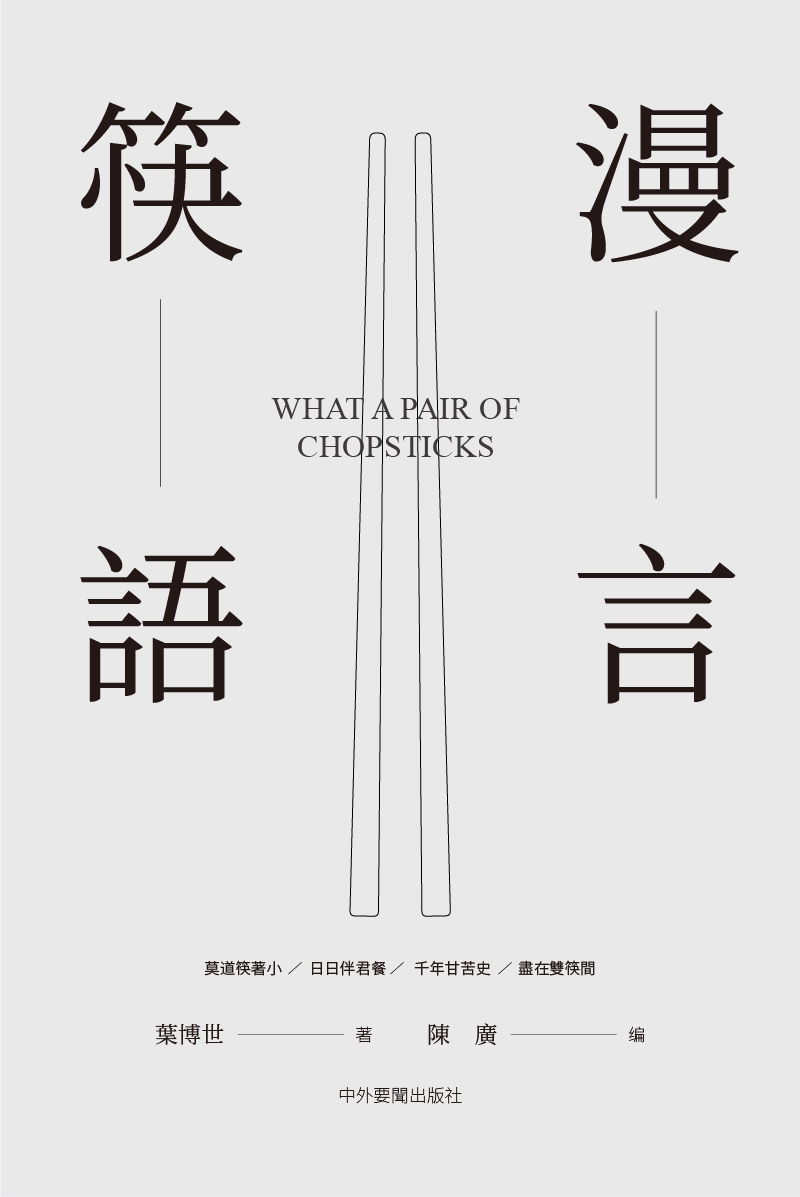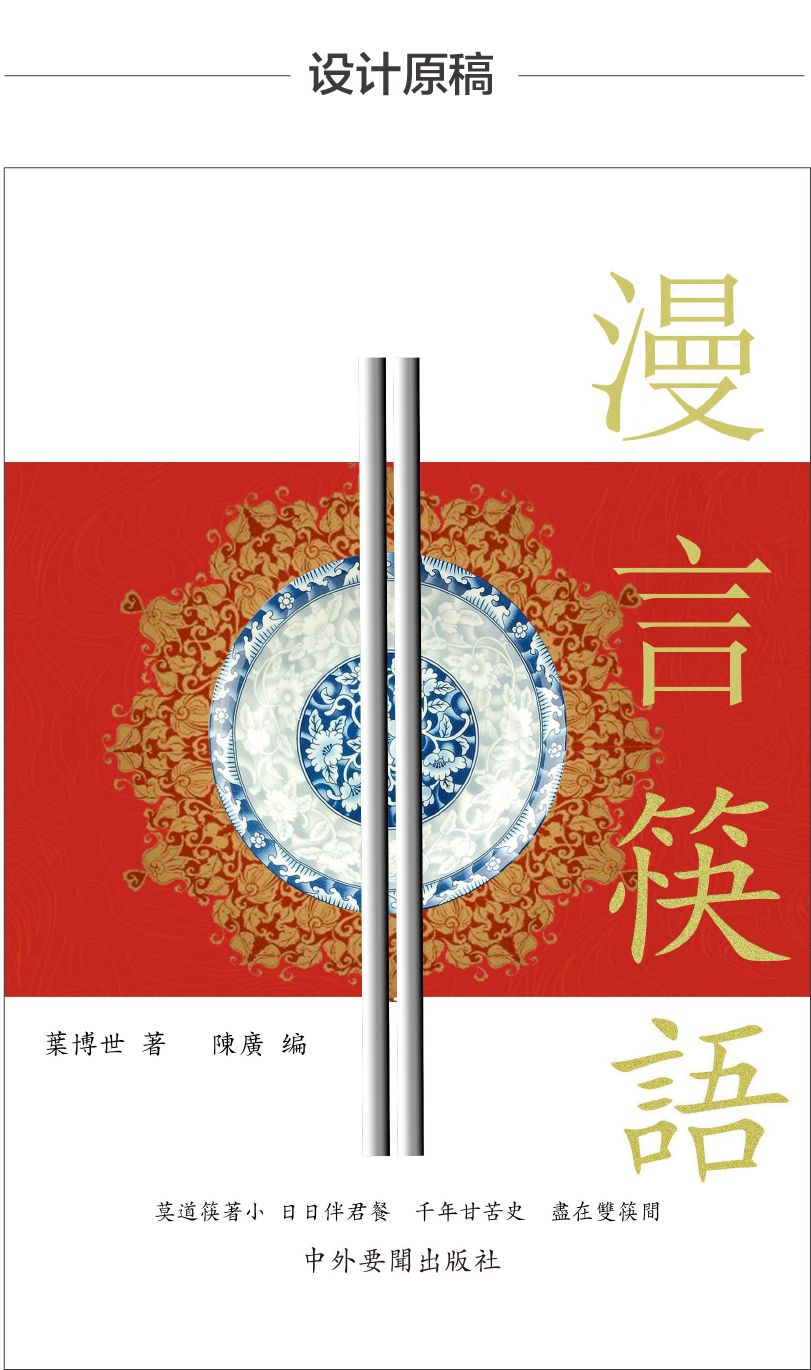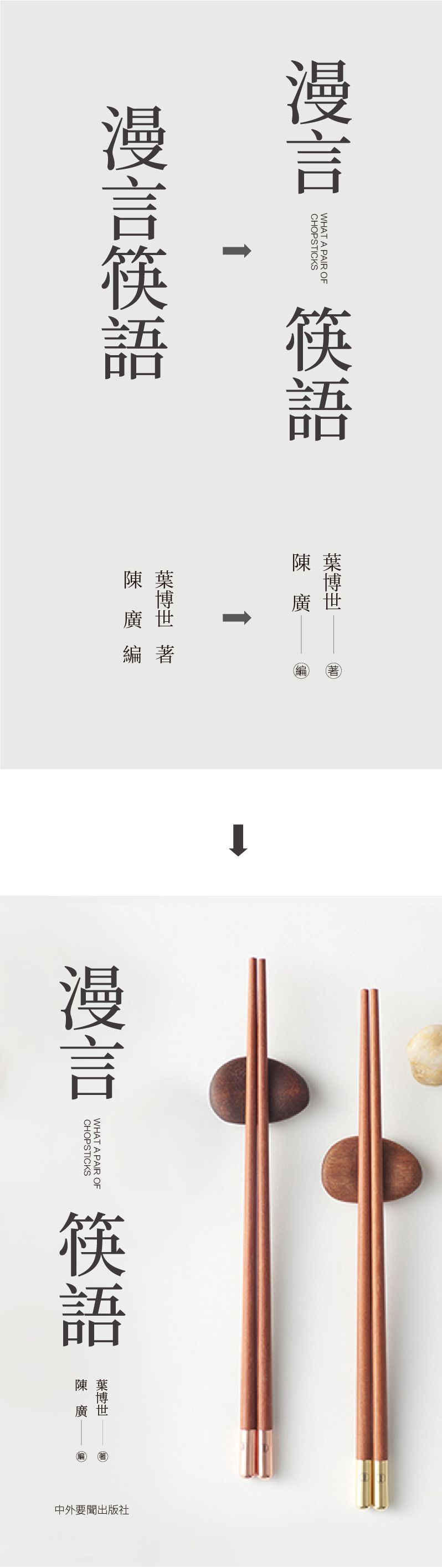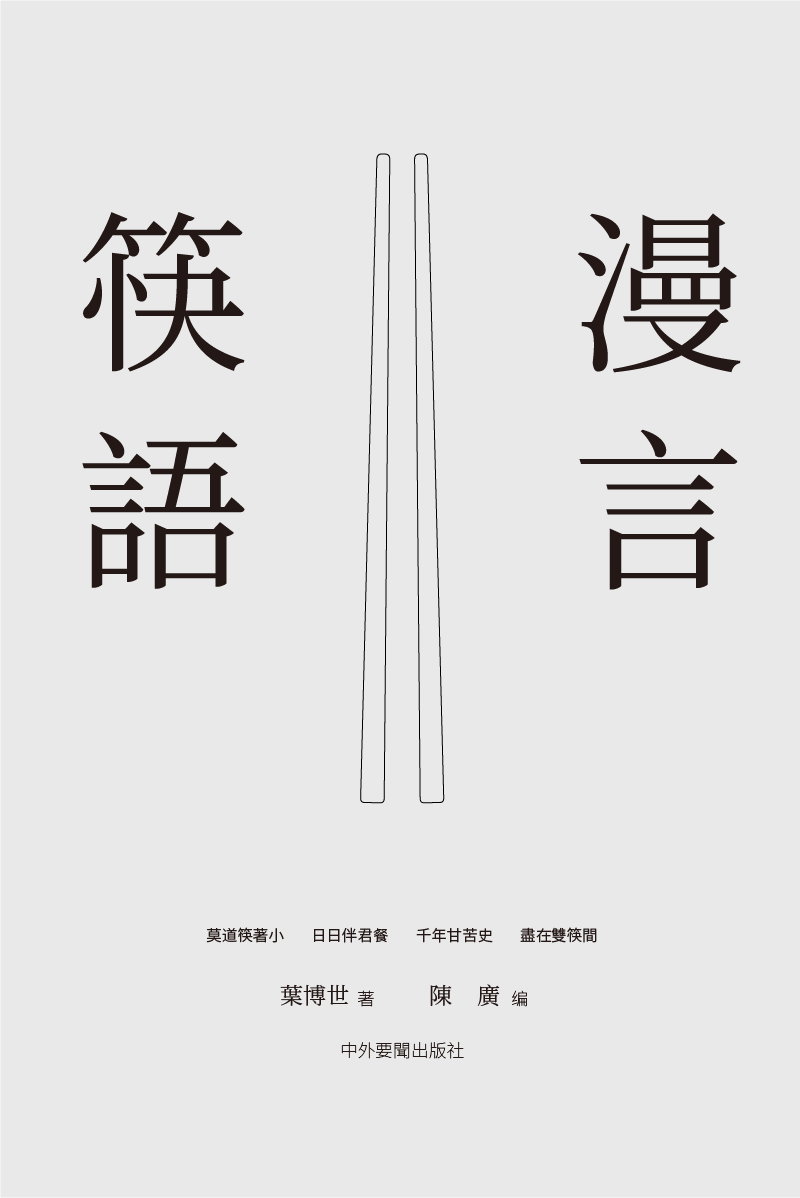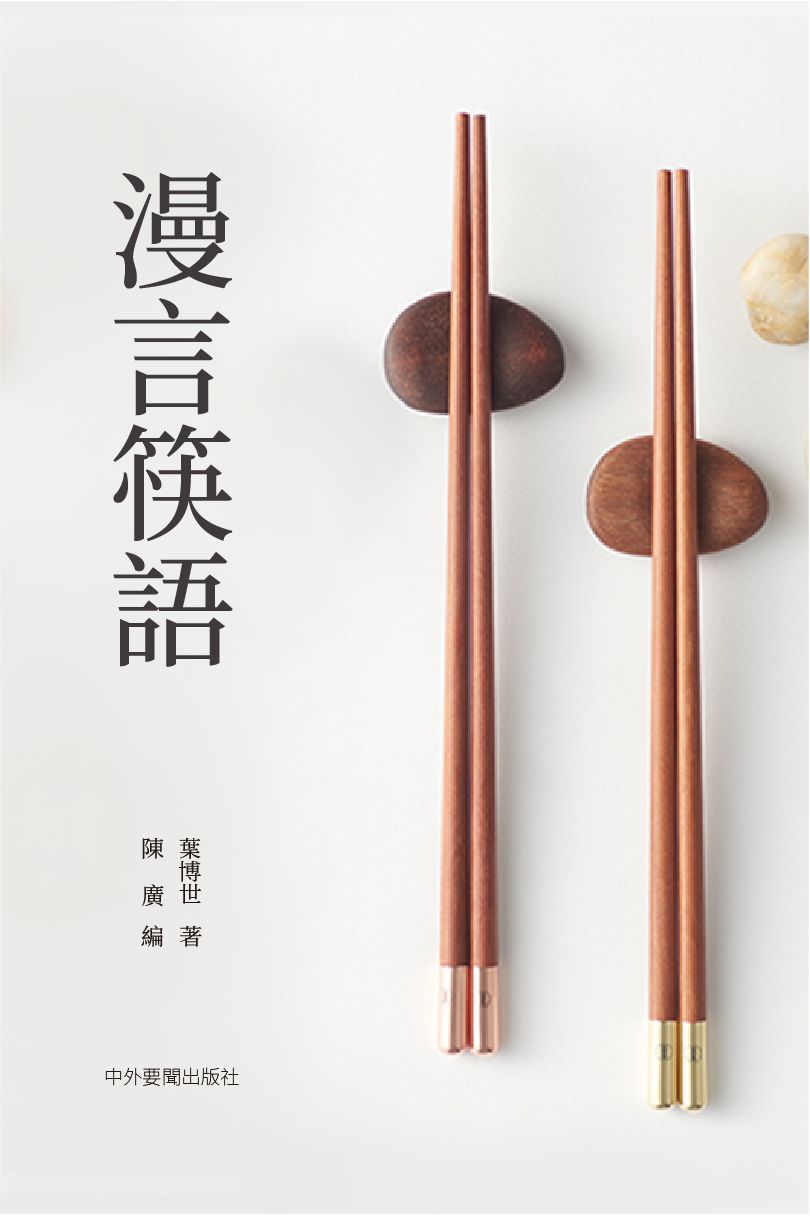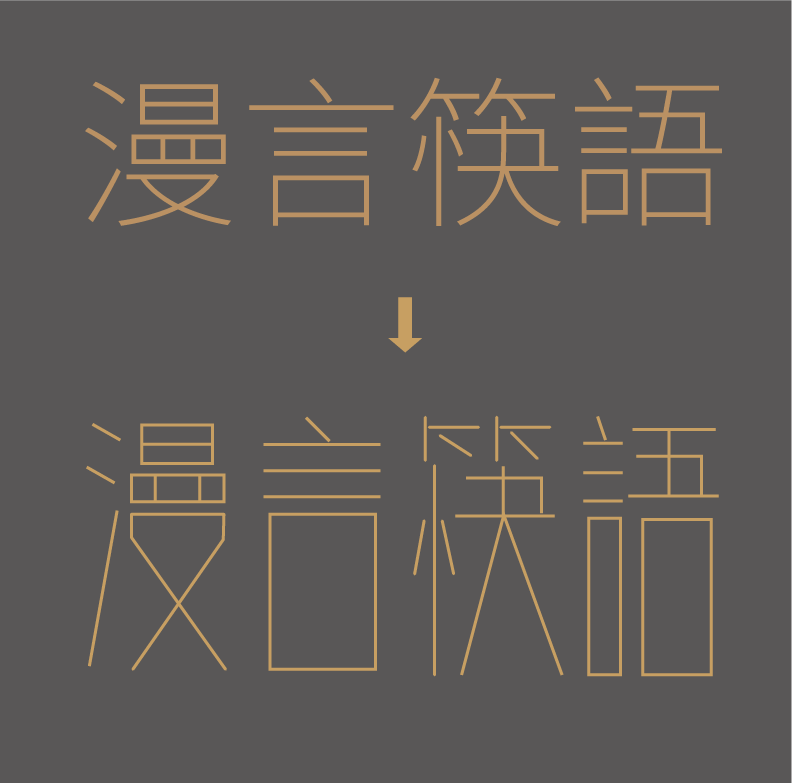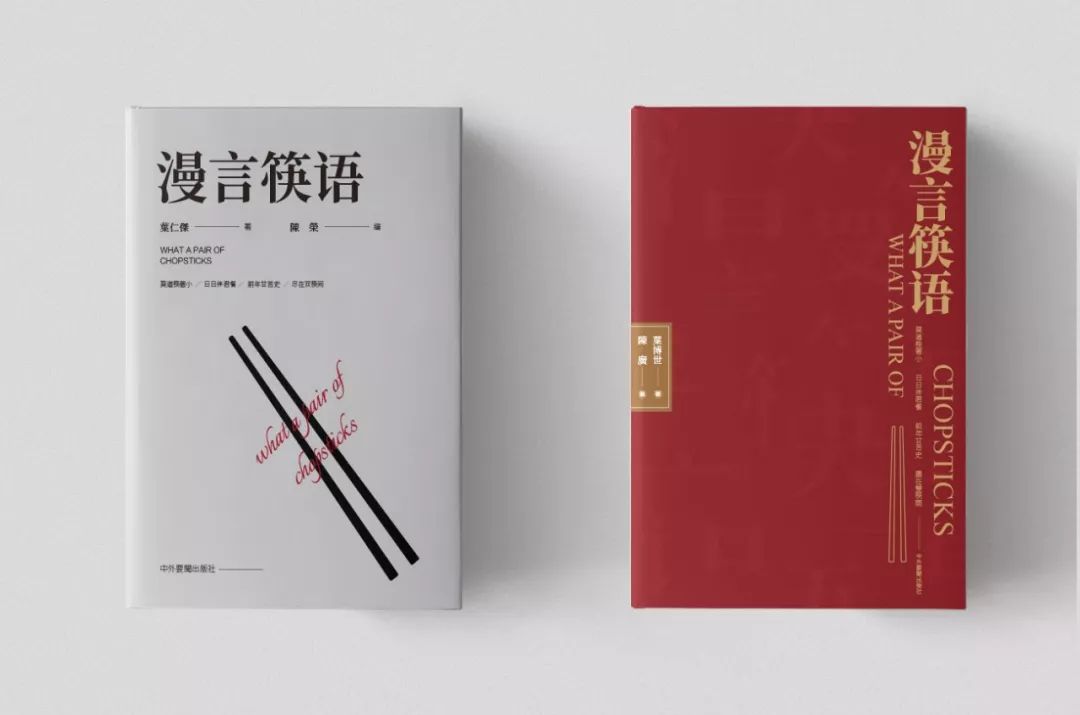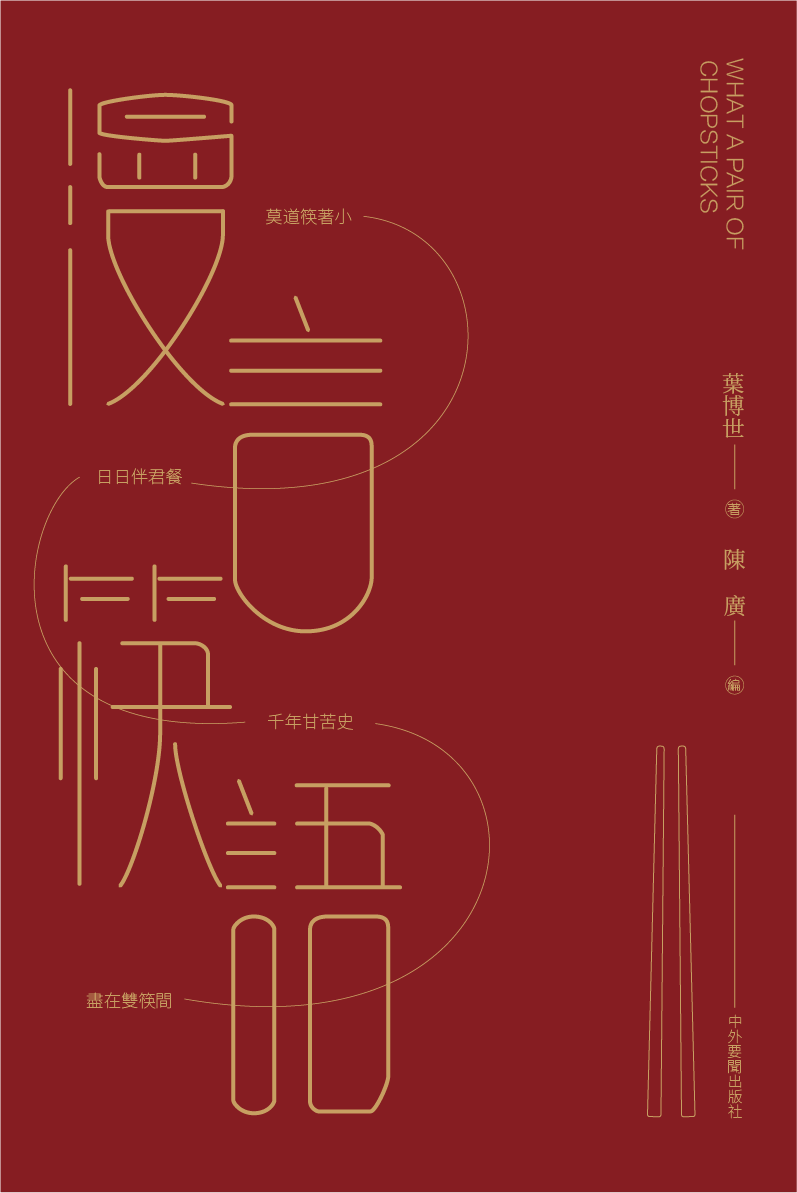
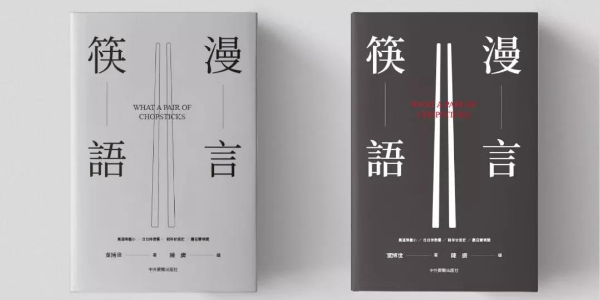
书籍封面怎么做?从三种一对一改稿开始
今天我们说说书籍封面的设计,比起张扬的海报,它更讲究版式、创意和高级感,毕竟一本书是要长期留存下来的,设计得不好可没有返工的机会,比如下面这张图:
乍一看有点乡村风,仔细一瞧,发现主体“筷子”,背景的“碗”、“花纹”都很粗糙,而且三个素材风格不统一;其次图像和文字大小比例也不合理,图像太抢眼,导致书名很大但识别性很弱;最后文字排版之间也没有关联,显得非常散乱。
那我们就针对这三个问题,进行改稿。通过书名可以知道这是一本从各方面来探讨筷子的书,再加上四句小诗分析,中式风格更显,那就寻找些参考资料。
根据定好的风格寻找合适的配图,比如下面这张,有筷子,颜色淡雅,给人一种宁静舒缓的文艺感。
裁切局部,筷子主体放在画面右方,左边留出空白处放文字信息。
进行文字信息的层级整理,主要分四个部分:书名、作者、导语、出版社。
根据定好的风格来选择字体:最重要的信息“书名”和“作者”使用宋体,人文感很符合本书的调性;“导语”和“出版社”则使用较细的黑体,体现书封设计的精致感。
“书名”和“作者”采用竖排,“出版社”放置在最下方,采用横排形成方向对比,所有信息居中对齐:
现在排版还比较呆板,尝试在细节上增加一些变化。在书名“漫言”“筷语”间,加入英文增加大小和距离的对比,作者和编者加入线条和线圈,丰富细节。
对于书封设计而言,图形起着辅助、引导、帮助理解主题的作用,但很多时候客户没有提供美观的图片,通过素材网也没有寻找到合适的配图,这时候就需要设计师根据主题,对图像素材进行提炼了。比如把筷子简化为线描效果,放置在画面中央作为主体元素,书名排列在两侧,其他元素放置在画面下方。
继续深入刻画,在筷子元素上方加入英文、“书名”和“作者”增加线条来丰富细节,一个较简约的设计就完成了:
尝试左右构图,如果觉得负空间留得较多,可以把书名笔画拆开作为底纹:
在没有合适配图的情况下,还有一招绝杀,就是使用字体设计作为画面的主体。以“思源黑体ExtraLight”为例,用钢笔工具勾勒出基本形态,再把字体下半部拉长,形成修长字形。
为了增加亲和力,在AI“描边”面板中把端点改为“圆头端点”,再用钢笔锚点工具把笔画转折处改为圆角处理。最后三点水、竖心旁、竹字头的“点”,统一改为直线。
最后将导语四句诗,像穿针引线一样,插在书名中,既增加了节奏,又起到引导阅读的作用。